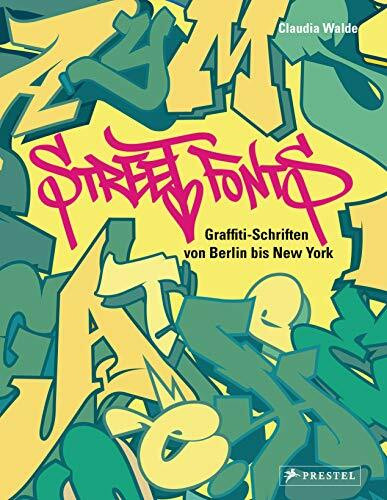
Street Fonts: Graffiti-Schriften von Berlin bis New York
"Street Fonts: Graffiti-Schriften von Berlin bis New York" von Claudia Walde ist ein faszinierendes Buch, das die Vielfalt und Kreativität der Graffiti-Kunst weltweit präsentiert. Die Autorin, selbst eine erfahrene Künstlerin in der Street-Art-Szene, hat über 150 Künstler aus verschiedenen Städten wie Berlin, New York, London und Tokio zusammengebracht. Jeder Künstler zeigt seine einzigartigen Schriftstile und erklärt die Inspirationen und Techniken hinter ihren Werken. Das Buch bietet nicht nur visuell beeindruckende Abbildungen von Graffiti-Schriften, sondern auch Einblicke in die kulturellen Hintergründe und die Bedeutung dieser Kunstform als Ausdruck urbaner Identität. Es ist eine Hommage an die dynamische Welt der Straßenkunst und eine Inspirationsquelle für Künstler und Kunstliebhaber gleichermaßen.
Claudia Walde, alias MadC, zählt zu den weltweit bekanntesten Graffiti-Künstlerinnen, ihre Arbeiten waren bereits in über 35 Ländern zu sehen. Im Prestel Verlag erschienen ihre Bücher Street Fonts ¿ Graffiti-Schriften von Berlin bis New York und Graffiti XXL: Street Art im Großformat.